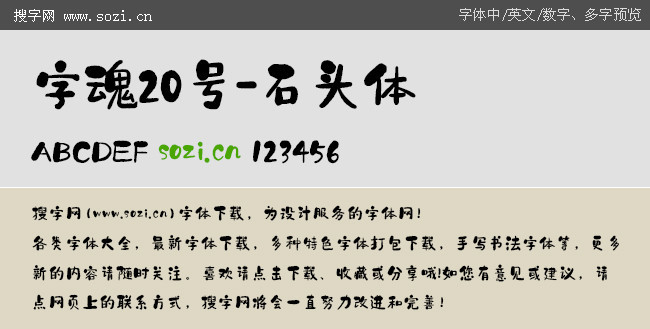
字魂20號(hào)-石頭體
搜字網(wǎng)提供一款字魂20號(hào)-石頭體中文字體下載,該字體是一款毛筆書法手寫字體,該字體包含6763個(gè)中文、字母、 符號(hào)和數(shù)字,具有可愛(ài)、卡通、創(chuàng)意、快樂(lè) 的風(fēng)格,可以滿足您設(shè)計(jì)上的各種需求,該字體主要用于企業(yè)店鋪、廣告、影視傳媒、游戲、動(dòng)漫 等場(chǎng)景。